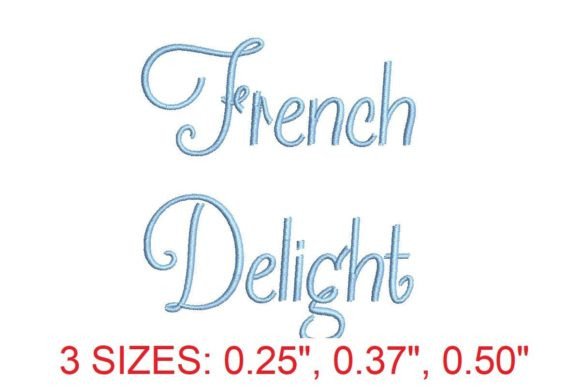
French Delight Embroidery Font
Jeśli szukasz wysokiej jakości materiałów, takich jak French Delight Embroidery Font, ten pakiet premium to fantastyczny wybór dla Twoich kreatywnych projektów.
Precyzyjnie wykonany, French Delight Embroidery Font zapewnia czyste wektory, płynną typografię i licencję komercyjną dla Twojego spokoju.
Niezależnie od tego, czy tworzysz produkty POD (druk na żądanie), zaproszenia ślubne czy grafiki do mediów społecznościowych, French Delight Embroidery Font będzie idealnym wyborem.